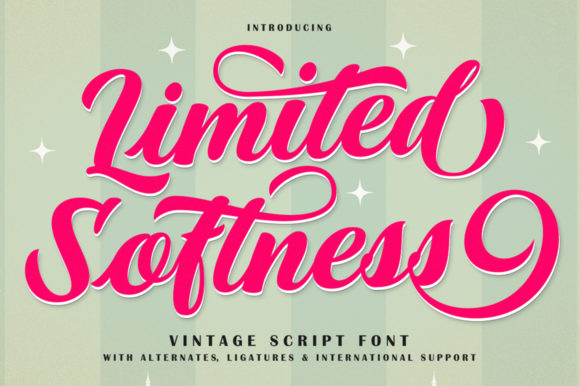
Limited Softness Font
Znalezienie odpowiednich elementów projektu może być wyzwaniem, ale Limited Softness Font oferuje wyjątkową kolekcję, która natychmiast ulepszy Twoją pracę.
Niezależnie od tego, czy tworzysz produkty POD (druk na żądanie), zaproszenia ślubne czy grafiki do mediów społecznościowych, Limited Softness Font będzie idealnym wyborem.